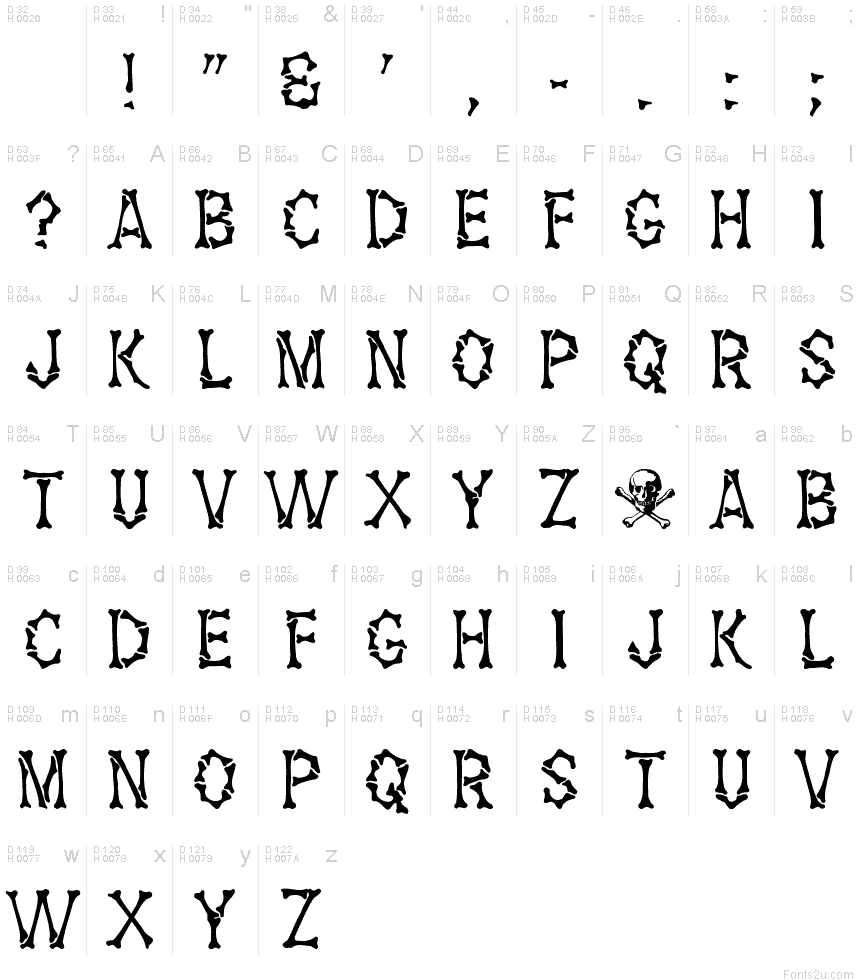
Headhunter di D. Rakowski è un carattere display gratuito in stile cartoon pauroso. Ogni lettera sembra scolpita in ossa tozze, con steli affusolati e nodi arrotondati, per un effetto giocoso e inquietante al tempo stesso, come un accessorio di Halloween sotto la luce nera. La spaziatura è stretta e ritmica: le parole si incastrano creando titoli spaventosi e leggibili che catturano l'attenzione fin da subito.
L'uso di Headhunter in grandi dimensioni rende poster, inviti a feste, stream horror, insegne di case stregate, grafiche per escape room e merchandise a tema spaventoso immediatamente d'impatto. Questo font gratuito della famiglia Headhunter brilla particolarmente se abbinato a un carattere sans serif pulito per il testo principale, lasciando che le forme ossee delle lettere conferiscano tutta la drammaticità necessaria a titoli e loghi.